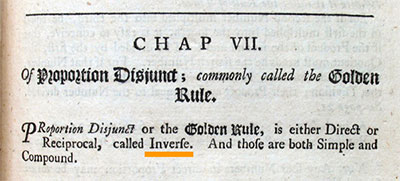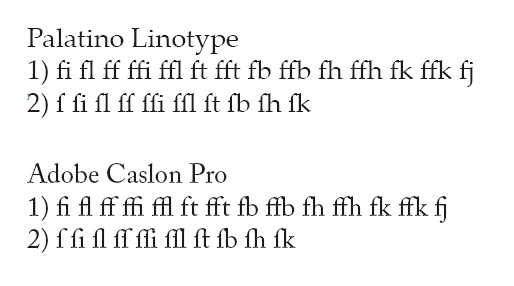
versehentlich habe ich sie schon benutzt, habe mich aber noch nie gefragt, welchem (besonderen?) Zweck sie eigentlich dienen. Ich meine hierbei natürlich nicht die Standard-Ligaturen, wie man sie aus jeder besseren Schriftart kennt. Ich meine diejenigen Ligaturen, bei welchen z.B. beim »f« der Balken nur auf der linken Seite angedeutet ist. Bei der ff-Ligatur kommt es auf diese Weise zwar ggf. zu einer Berühung der beiden Köpfe, der Balken zwischen den beiden fs wird hingegen ausgespart. Diese Ligaturen findet man nur in besonders reichhaltig ausgebauten Schriften und sie sind immer zusammen mit den regulären Ligaturen vorhanden.
Wann kommt es zum Einsatz dieser speziellen Ligaturen? Aufgefallen sind mir die noch nie ... :lol:
Für mich ist der eigentliche Sinn einer Ligatur Räume zu optimieren.
Zum Beispiel die "Th" Ligatur lasse ich mir manchmal gefallen. Bei Schriften, wo es ansonsten blöde aussehen würde, wenn T und h kollidieren, wenn man die Laufweite verringert.
Und dann gibt es ja noch "Blumiges", wie die "ct"- und die "st"-Ligatur mit den ausschmückenden "Kringels oben". Die sind wohl für Amerikaner gedacht, die mögens ja ein bissl blumiger :P. Um auch innerhalb der Wörter zu stylen, eine Note zu hinterlassen.
Ich meine diejenigen Ligaturen, bei welchen z.B. beim »f« der Balken nur auf der linken Seite angedeutet ist. Bei der ff-Ligatur kommt es auf diese Weise zwar ggf. zu einer Berühung der beiden Köpfe, der Balken zwischen den beiden fs wird hingegen ausgespart.
Öhm, wenn ich dich jetzt nicht völlig falsch verstehe, beschreibst du keine f-Ligaturen, sondern lang-s-Ligaturen, oder? Der Balken nur links angedeutet und rechts nicht vorhanden. Das wäre ein lang-s und es gibt in der Tat einige gut ausgebaute Schriften mit jeder Menge lang-s-Ligaturen.
@Ralf: Das könnte genau sein. Mir ist bisher einfach noch kein lang-s bei einer Antiqua untergekommen. Bei den gebrochenen Schriften hätte ich damit ja keine Probleme gehabt, aber bei einer Antiqua wäre ich darauf im Leben nicht gekommen!
es gibt halt viele leute die ueberall ligaturen reinknallen -
auch da wo sie fehl am platz sind. indesign unterstuetzt
sowas ja auch noch!
In diesem Zusammenhang hatte ich ja letztens die interessante Diskussion, ob man bei Unwissenheit über den Einsatz von Ligaturen besser einfach alle immer setzt, oder den Satz von Ligaturen besser ganz ausschaltet. Kam natürlich über eine Word-LaTeX-Diskussion zustande. Kaum jemand kennt die Regeln für Ligaturen. InDesign und Latex machen sie einfach automatisch überall und ich muß manuell nachhelfen, wenn ich sie unterbinden will. Word, OpenOffice etc. machen sie einfach nicht. Prozentual sind natürlich mehr richtige als falsche Ligaturen in einem InDesign- oder Latex-Dokument, aber besser macht es das irgendwie auch nicht. Was soll man Laien jetzt empfehlen?
Naja, ich schreibe viel Englisch, da kann man zumindest Standard-Ligaturen getrost immer zulassen ... :twisted:
>Mir ist bisher einfach noch kein lang-s bei einer Antiqua untergekommen
2 digitale Schriften mit lang-s Ligaturen (2) als Beispiel
BTW ich habe selbst noch nie ein Antiqua lang-s, geschweige denn eine lang-s Ligatur eingesetzt.
ich halte die deutsche Regel, dass Ligaturen bei zusammengesetzten Wörtern nicht verwendet werden dürfen, für eine Kopfgeburt. Ein i-Punkt der mit einem Überhang eines Worte kollidiert sieht besch… aus ob der Umfall im Wort oder zwischen zwei zusammengesetzten geschieht. Aus diesem Grund ignoriere ich diese Regel in der Regel.
Lustig wäre aber sicher eine drei-f-Ligatur für beispielsweise Schifffahrt. ;-)
Eine Ligatur bildet eine visuelle und zwangsläufig auch sprachliche Einheit. Wenn das auf eine Wortfuge fällt, kommt man beim Lesen in stolpern. Einfach ausprobieren!
Aufliegen liest sich prima – aber aufliegen (man denke sich die Ligatur) wird zu au-fliegen. Bei Schifffahrt kann eine Ligatur sogar hilfreich sein, eine ff-Ligatur versteht sich. Das würde die Lesbarkeit sogar verbessern.
Gerade bei den neueren Groteskschriften ist das f doch ohnehin meist so gestaltet, dass es gar keine Kollisionen mehr gibt und die fl- und fi-Ligaturen sind nur aus Gründen der Kompatibilität enthalten und richten nicht selten mehr Schaden als Nutzen an. Bei solchen Schriften würde ich die Ligaturen – zumindest im Fließtext – einfach abschalten. Inhalt geht wie immer VOR typografischer Finesse.
Ein i-Punkt der mit einem Überhang eines Worte kollidiert sieht besch… aus ob der Umfall im Wort oder zwischen zwei zusammengesetzten geschieht. Aus diesem Grund ...
... sollte man die Regel hier auch nicht ignorieren, wie Ralf ja schon überzeugend dargelegt hat, sondern dann muß man eben an dieser Stelle etwas spationieren.
Ralf, ich glaube das einfach nicht.
Wenn du mir eine empirische (am besten mehrere, weil einzelne wissenschaftliche Tests haben schon oft ›bewiesen‹ was später widerlegt wurde) nennst die das untermauert, dann will ich mich gerne bessern. Aber bis dahin halte ich’s mit Buddha: »Glaube nix, nur weil Andere es dir erzählen!«
@Ralf: Was du über deine Erfahrung schreibst, gilt auch für mich umgekehrt. Ich kann mich nicht erinnern jemals über eine Ligatur in einer Fuge gestolpert zu sein.
Die Sache mit den Wortbildern bzw. unserer Art nachzulesen interessiert mich jedoch. Diese Theorie wird ja quasi in allen Werken über Typografie vertreten. Kannst du mir eine Referenz nennen, wo ich mehr darüber erfahre was du hier beschreibst?
Natürlich gilt für mich auch hier: Am Ende muss man von Fall zu Fall entscheiden.